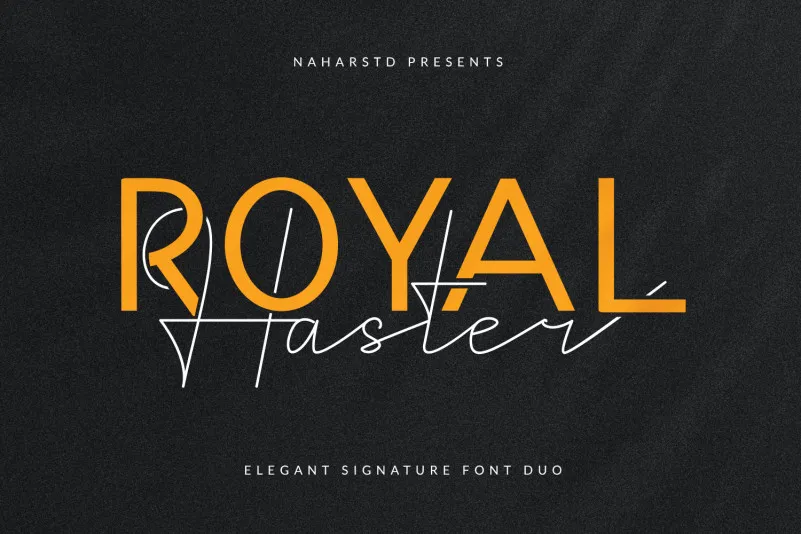
Royal Haster Font Duo – Download Grátis
A Royal Haster Font Duo é uma elegante escolha para designers que valorizam a simetria e a fluididade no design. Com seus traços suaves e curvas arredondadas, essa fonte é perfeita para criar designs de marcas, logos, letras e logotipos com um toque sofisticado. Seu uso também pode ser visto em etiquetas de roupas, editoriais de revistas, embalagens, postais, sacolas de shopping, camisetas personalizadas, capas de livros, e até mesmo em eventos especiais ou qualquer projeto gráfico. Este conjunto de fontes é uma opção confiável para quem busca uma fonte que combine elegância com facilidade de uso, fazendo-a perfeita para um amplo espectro de aplicativos design.